同シリーズの前回記事でフィットフォントの技術を利用して書体開発・提供を行なった事例として「Alpine AXIS」をご紹介しましたが、2つめの事例はDENSOのコーポレートフォントのプロジェクトです。
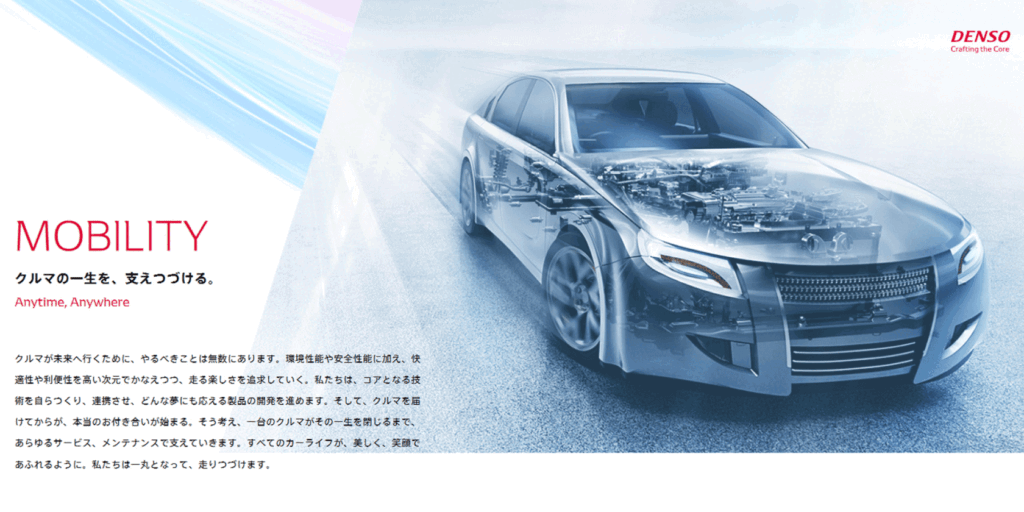
この事例では、タイププロジェクトの和文フォントと企業側が指定した欧文フォントを組み合せた「組み合わせフォント」を提供しました。タイププロジェクトのAXISフォントのウェイトがKontrapunktによってデザインされた欧文フォントに合わせて調整され、エンジニアリングによって欧文フォントは和文フォントの中に組み込まれ、最終的に1つのフォントデータとして提供されました。